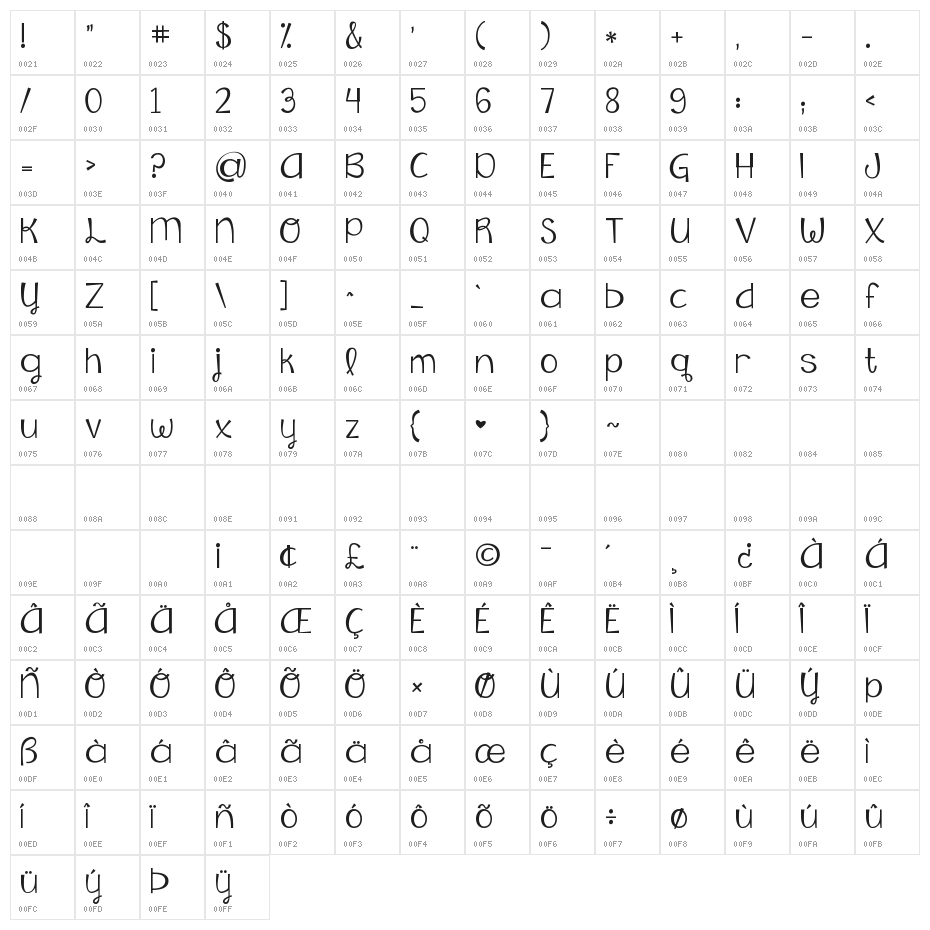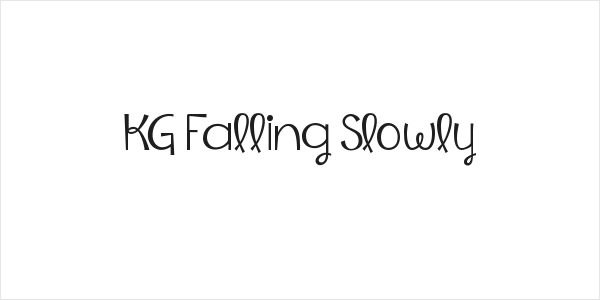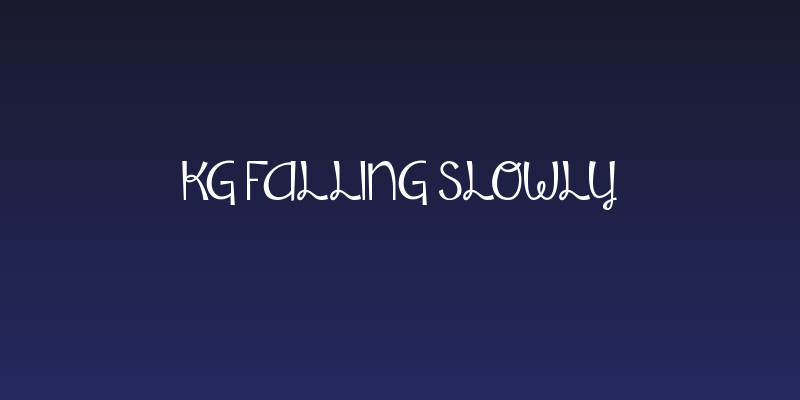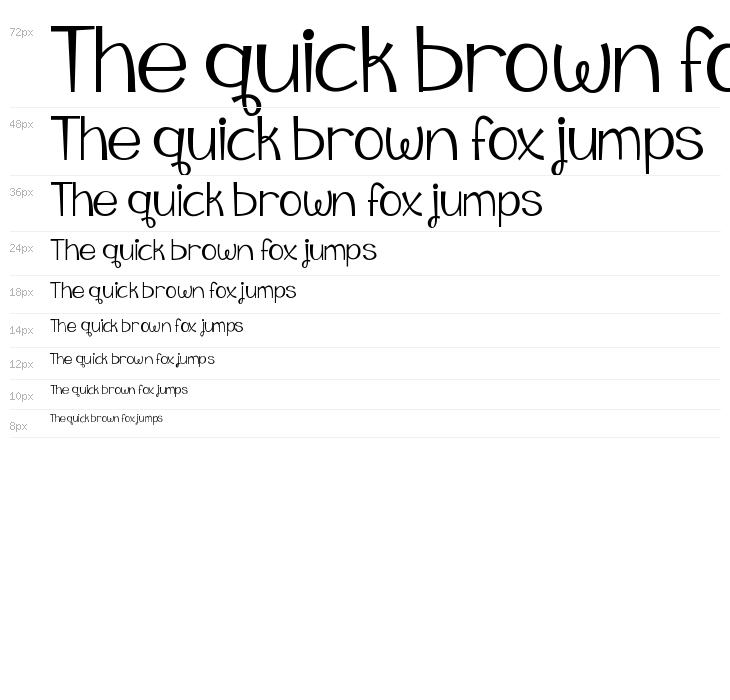
KG Falling Slowly Font
| Stile generale | Playful, Whimsical |
| Caso d'uso | Headlines, Logos, Creative projects |
| Progetti proposti | Ideal for children's books, playful branding, greeting cards, and creative posters. |